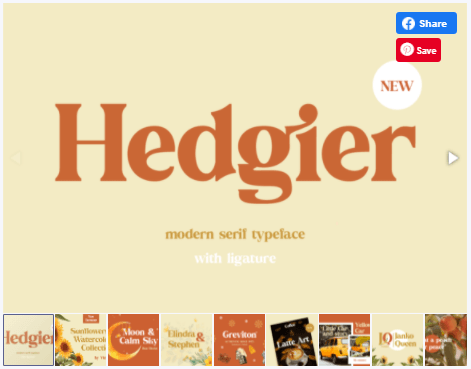
Hedgier Font
Hedgier - это современный, модный и шикарный шрифт с засечками. Его стильные альтернативы и лигатуры делают этот шрифт идеальным для любого проекта. Добавьте его к своим любимым творениям и позвольте себе удивиться полученному результату.